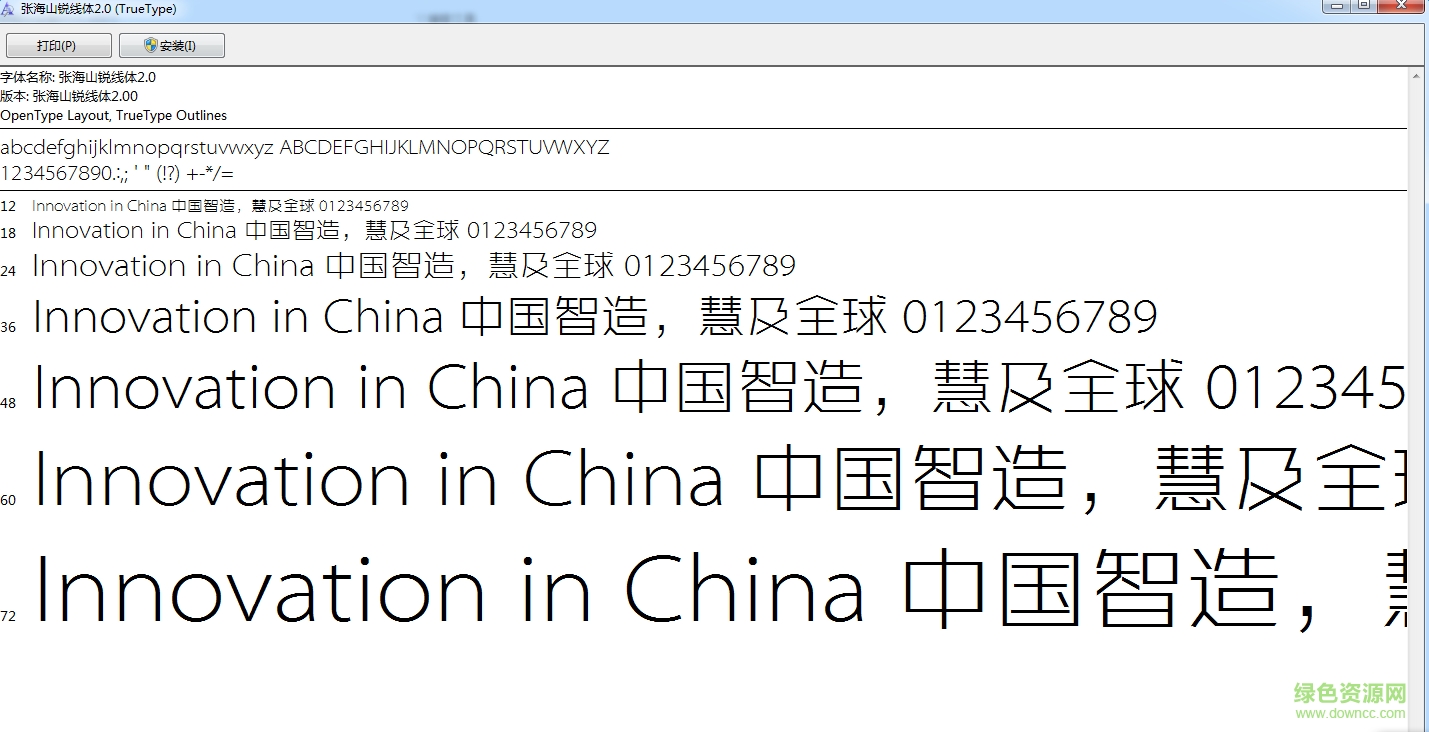
2.0 regular是什么字體?2.0 regular字體是一款便于閱讀和識(shí)別的常規(guī)字體,該字體一筆一畫工工整整,視覺特征突出,非常實(shí)用,需要的小伙伴快來下載吧!
經(jīng)過精心設(shè)計(jì)的標(biāo)準(zhǔn)字體與普通印刷字體的差異性在于,除了外觀造型不同外,更重要的是它是根據(jù)企業(yè)或品牌的個(gè)性而設(shè)計(jì)的,對策劃的形態(tài)、粗細(xì)、字間的連接與配置,統(tǒng)一的造型等,都作了細(xì)致嚴(yán)謹(jǐn)?shù)囊?guī)劃,比普通字體相比更美觀,更具特色。